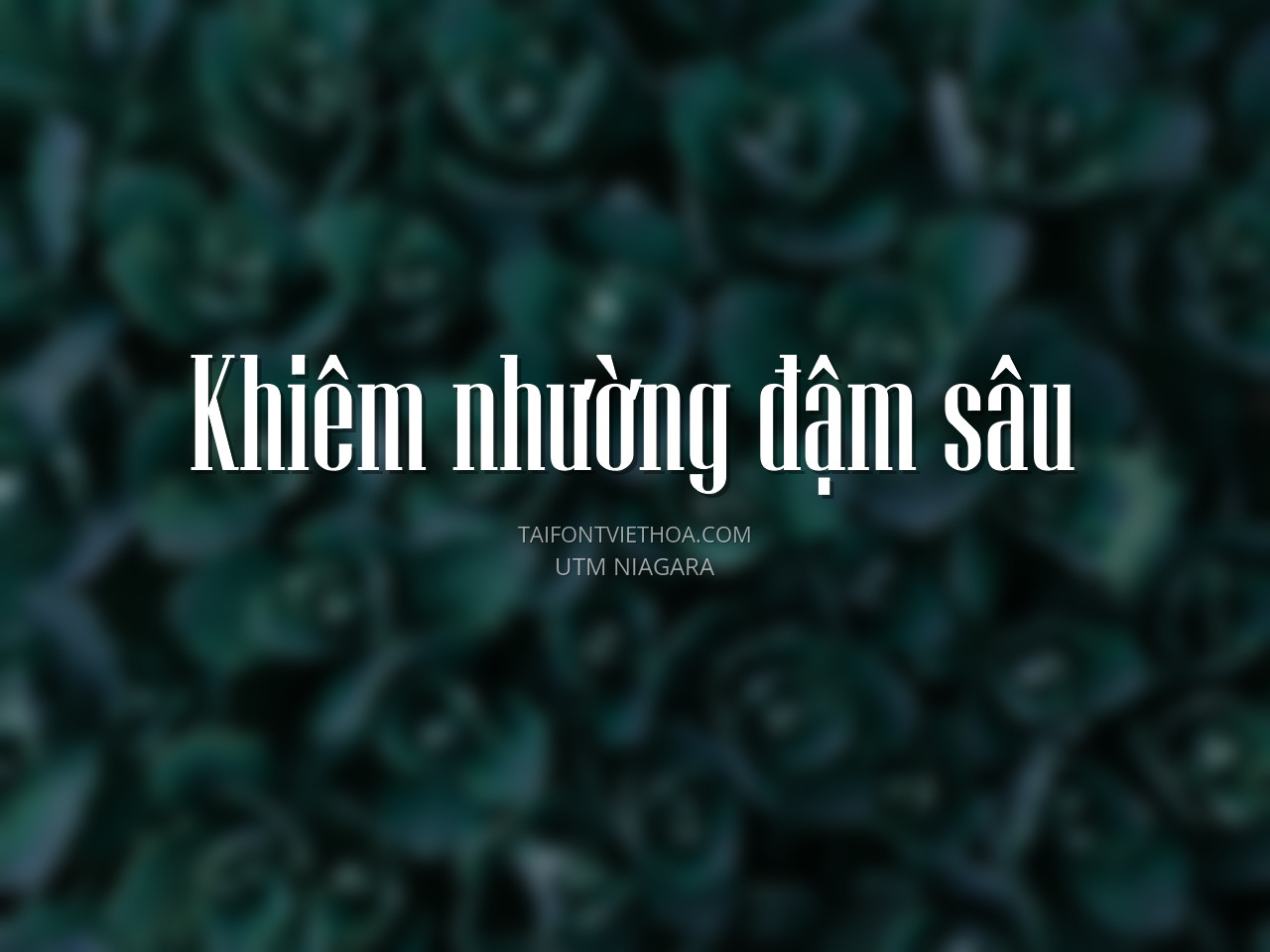
Giới thiệu về font UTM Niagara
UTM Niagara là phiên bản Việt hóa của font Niagara – một kiểu chữ serif mang phong cách cổ điển và trang nhã, được thiết kế để mang lại sự lịch lãm và tinh tế trong các dự án thiết kế thương hiệu và truyền thông. Font gốc nổi bật với các nét chữ có chân (serif) thanh thoát, tỉ lệ cân đối và độ tương phản hài hòa, rất phù hợp cho các ấn phẩm in ấn và quảng cáo cao cấp. Phiên bản Việt hóa đã được hoàn thiện để hỗ trợ đầy đủ tiếng Việt cùng hơn 200 ngôn ngữ khác, mở rộng khả năng ứng dụng trong nhiều lĩnh vực thiết kế đa dạng.
Đặc điểm thiết kế và ứng dụng của UTM Niagara
UTM Niagara sở hữu cấu trúc serif với các nét chân chữ thanh thoát, mềm mại và thiết kế hài hòa. Font có nhiều biến thể trọng lượng, giúp các nhà thiết kế linh hoạt sử dụng trong nhiều bối cảnh từ tiêu đề nổi bật đến nội dung chi tiết. Thiết kế font mang lại cảm giác dễ đọc, trang nhã và chuyên nghiệp.
Font thích hợp sử dụng trong thiết kế sách, tạp chí, thiệp cưới, danh thiếp, bao bì sản phẩm sang trọng và các ấn phẩm thương hiệu cao cấp. Các ngành nghề phù hợp gồm: xuất bản, thời trang, tổ chức sự kiện, nghệ thuật, giáo dục và thiết kế nội thất.